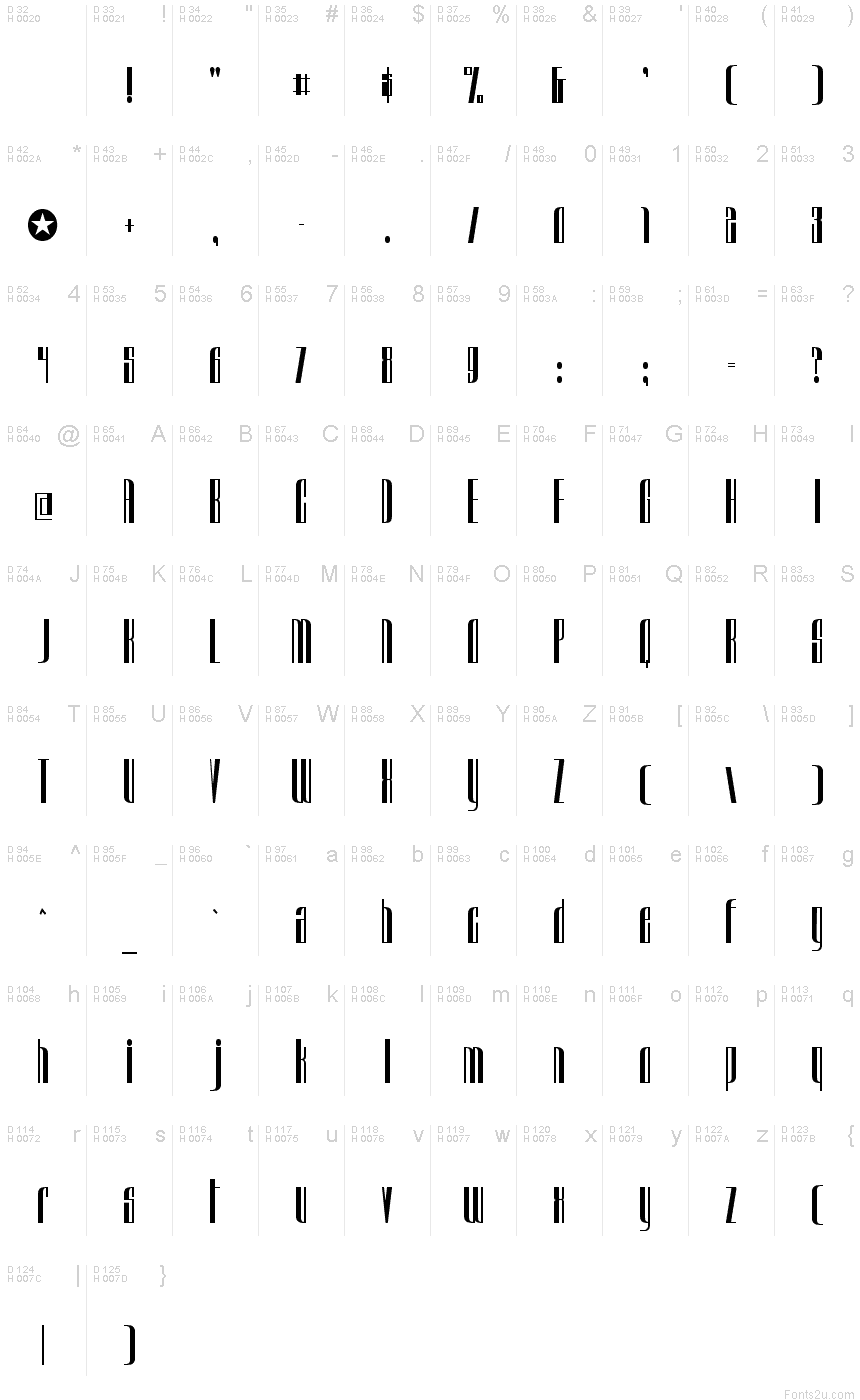
Urkelian Television Dynasty di Ray Larabie è un font display gratuito in stile TV retrò, caratterizzato da un'eleganza slanciata ispirata all'Art Déco. Le lettere si sviluppano in tratti verticali sottili e curve nette, conferendo al font un ritmo elegante e leggermente eccentrico, che sembra provenire direttamente dalla sigla di una sitcom di fine anni '80 o inizio anni '90.
È perfetto laddove quel tocco nostalgico è fondamentale: titoli di poster, branding ispirato alle sitcom, copertine di fanzine, cartelli di apertura e merchandising a tema si adattano perfettamente a questo font gratuito. Grazie alle sue forme alte e snelle, funziona egregiamente anche per nomi brevi, titoli di copertina e iniziali in stile monogramma, dove la sua silhouette stretta sa farsi notare.